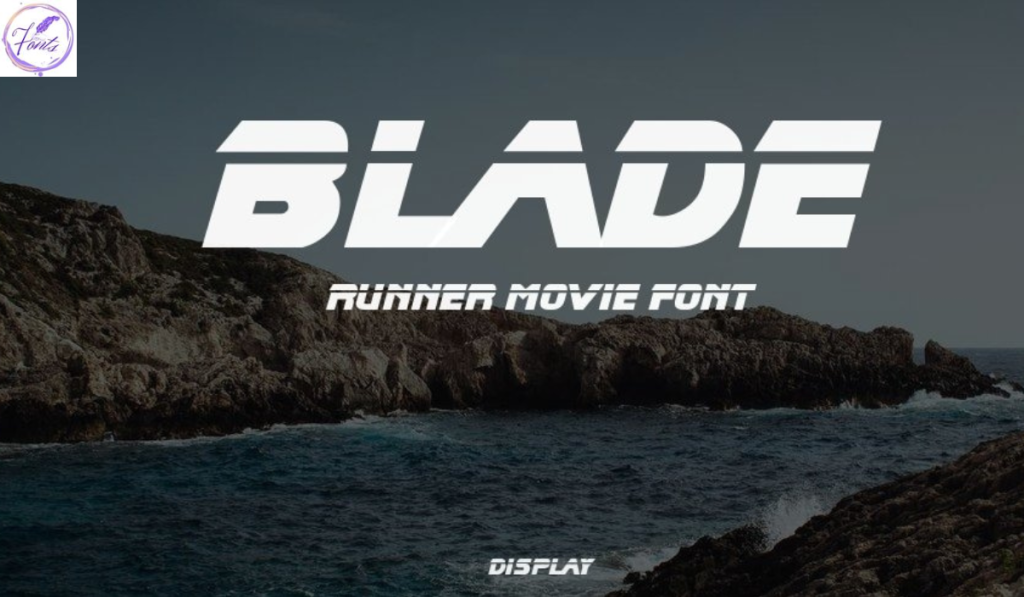
Blade Runner Movie font việt hóa
Tác giả: Phil Steinschneider
Bộ Font: Blade Runner Movie Font
Phân loại: Cá tính, độc đáo
Kiểu chữ: Không chân
Blade Runner Movie Font là một kiểu chữ độc đáo, được lấy cảm hứng từ bộ phim khoa học viễn tưởng nổi tiếng Phil Steinschneider ra mắt vào năm 1982. Font này được thiết kế bởi nhóm tác giả tài năng với mục tiêu tái hiện lại không khí tương lai và bí ẩn của bộ phim. Với những đường nét góc cạnh và mạnh mẽ, blade runner movie font mang đến cho các thiết kế của bạn một cảm giác hiện đại và đầy phong cách. Font này phù hợp cho các dự án thiết kế poster, tiêu đề, và các ấn phẩm kỹ thuật số.